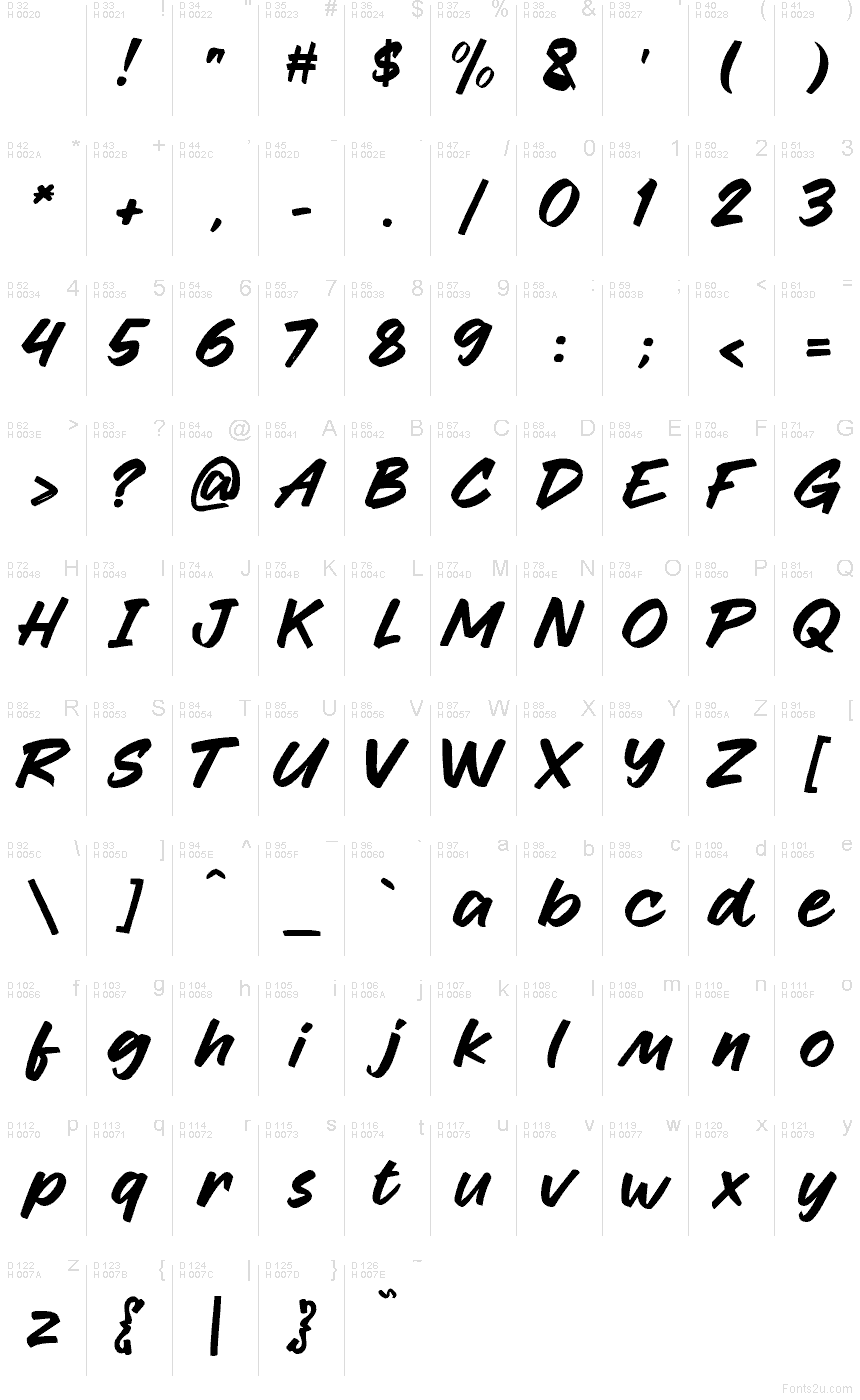
Frosty Fresh من BlackFridayFont هو خط فرشاة مجاني بإيقاع سريع وانسيابي، مع منحنيات ناعمة ودائرية تحافظ على مظهر الحروف عفوياً بعيداً عن التكلف. تبدو ضربات الخط وكأنها رُسمت بثقة باليد، مما يضفي على التصميم لمسة عفوية تحافظ على طابعها الجرافيكي دون أن تبدو قاسية أو مصطنعة.
تتناسب هذه الحيوية بشكل مثالي مع ملصقات المشروبات، لافتات المقاهي، اقتباسات وسائل التواصل الاجتماعي، التغليف، وعناوين الملصقات القصيرة، حيث تضفي ملمس الخط اليدوي السريع طابعاً مباشراً على الرسالة. كما يمكن استخدام Frosty Fresh في تصاميم الهدايا (Merch) أو العروض الموسمية، خاصة عندما ترغب في أن تبدو الكلمات الكبيرة وكأنها رُسمت بضربة واحدة سريعة بدلاً من أن تكون مصممة بعناية فائقة.